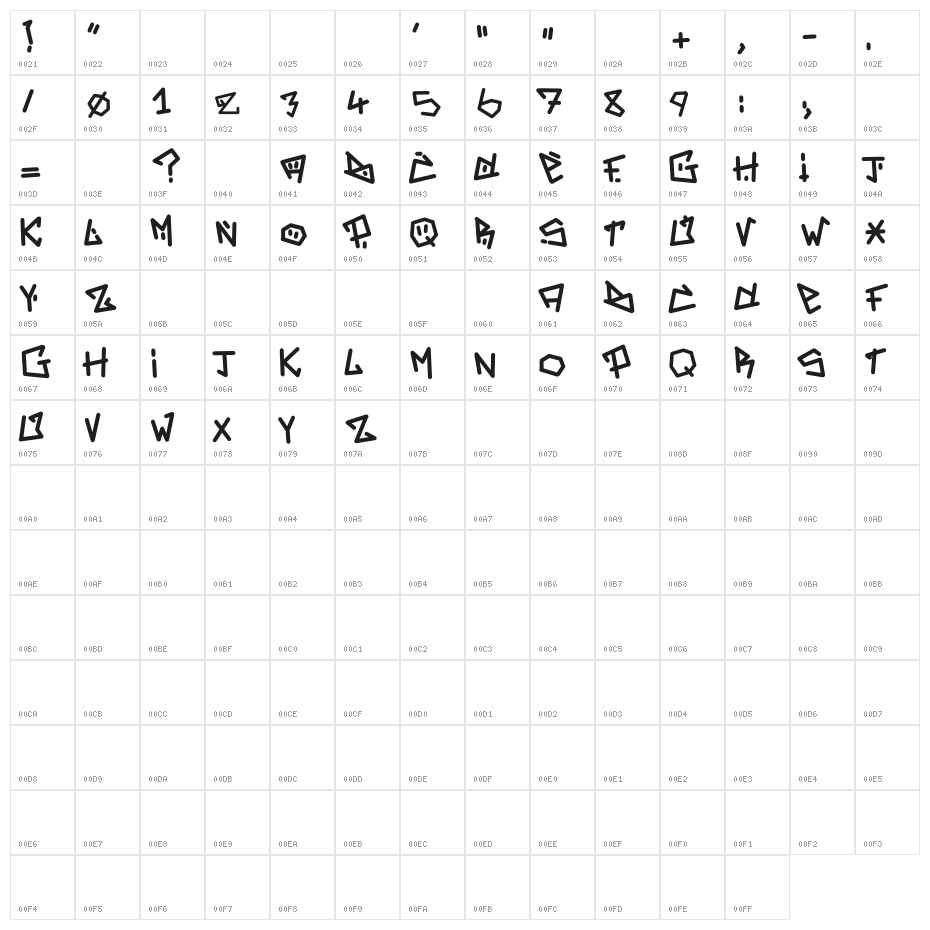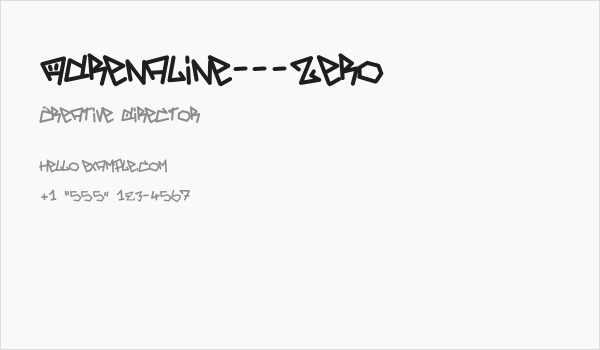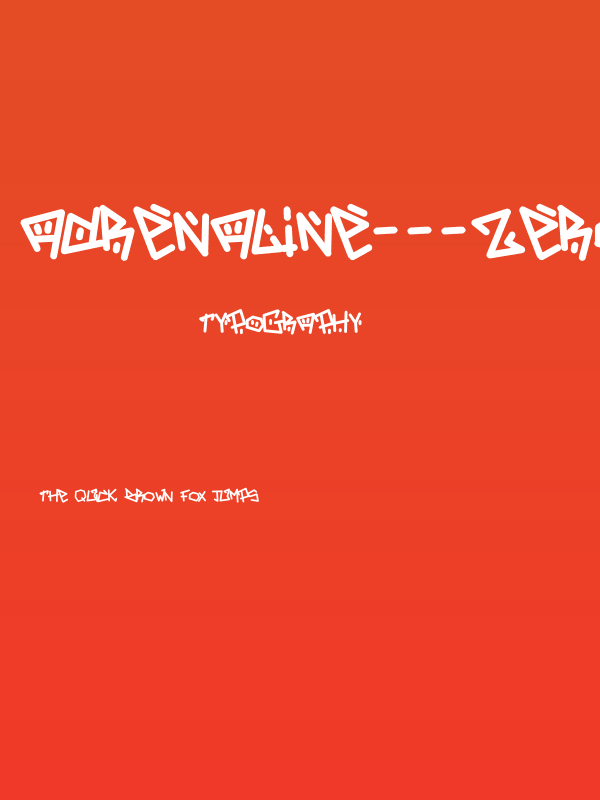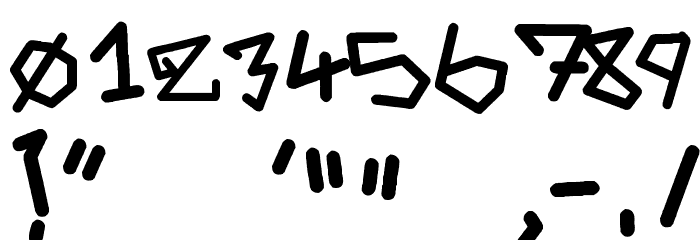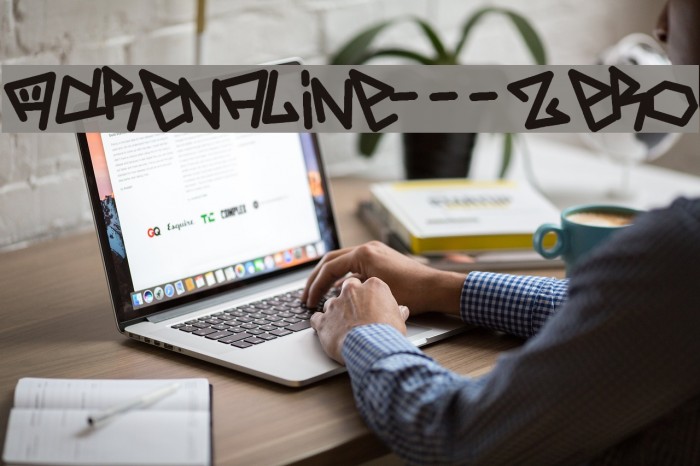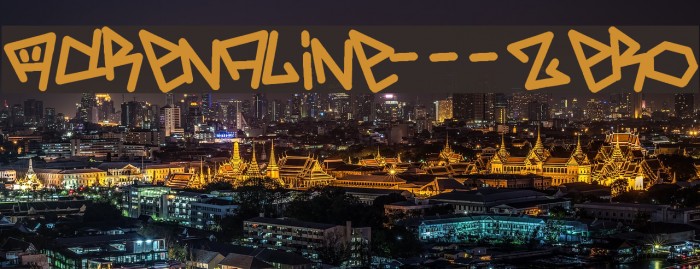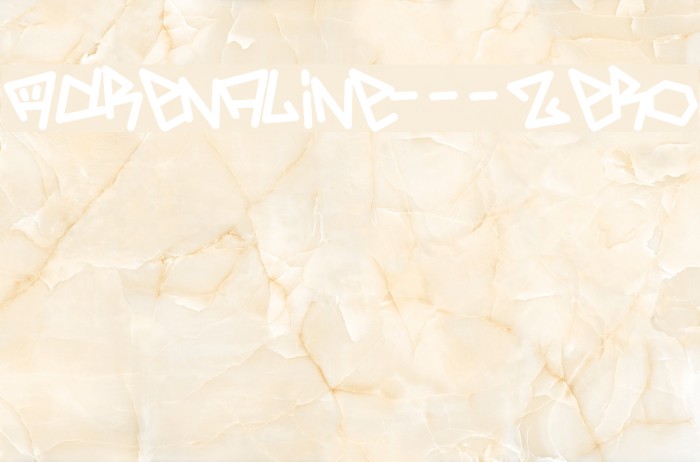
Adrenaline---Zero Font
| Gesamtstil | Modern, Urban, Edgy |
| Vorgeschlagene Projekte | Ideal for street art designs, music album covers, urban-themed posters, and edgy branding projects. |